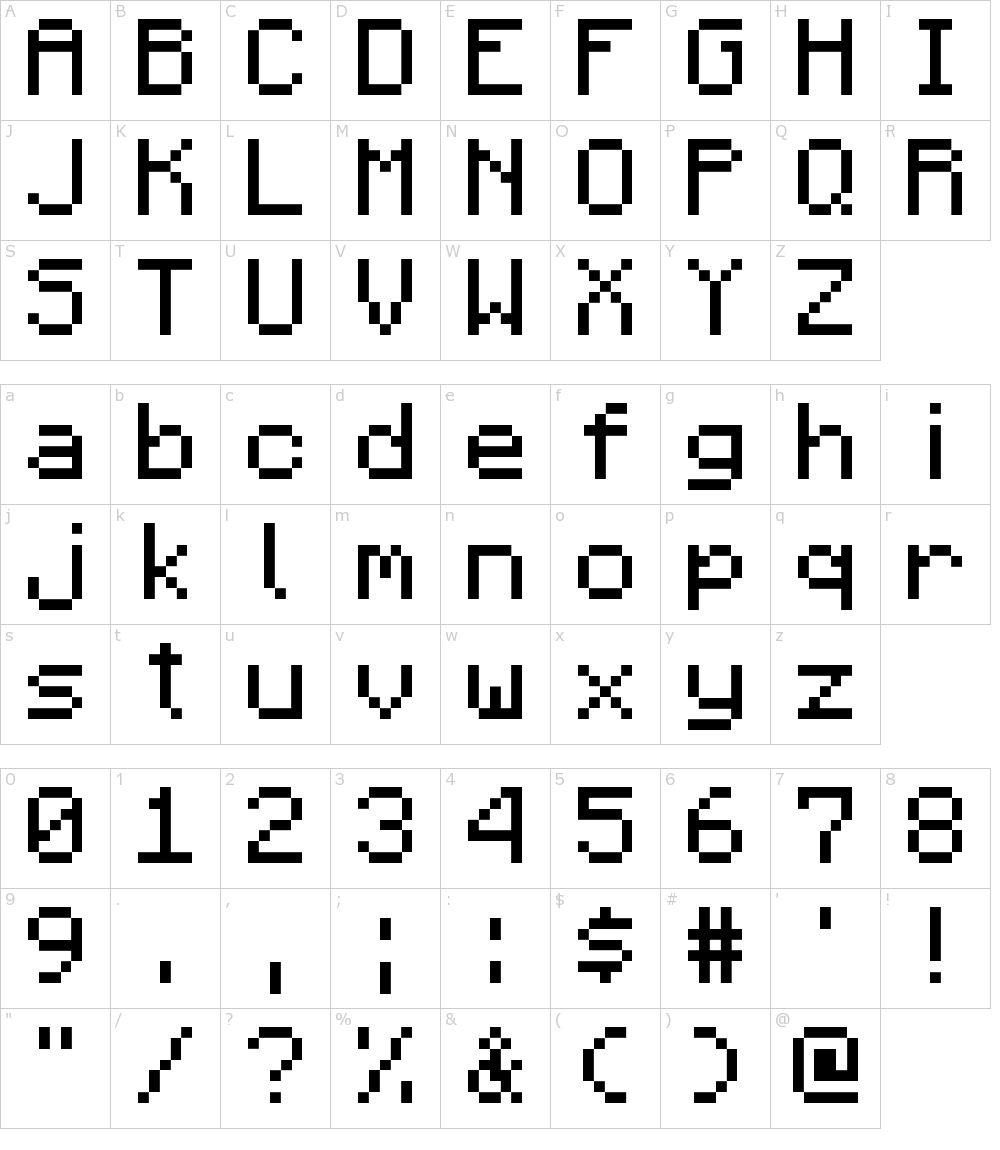
Phân loại: Độc đáo
Kiểu chữ: Sans-Serif
Độ dày: Thin, Light, Regular, Medium, Bold, Black
Font Minecraft là một font chữ đặc trưng, gắn liền với tựa game nổi tiếng cùng tên, được biết đến với phong cách pixel art đặc trưng. Font chữ này tái hiện hoàn hảo giao diện pixelated của trò chơi, mang đến cảm giác hoài cổ và đơn giản, gợi nhớ đến thiết kế đồ họa 8-bit cổ điển. Font Minecraft là font chữ thuộc bộ font chữ design thường được sử dụng trong các thiết kế liên quan đến game, đặc biệt là khi muốn tạo ra sự kết nối trực tiếp với thế giới blocky và sáng tạo của Minecraft. Đây là lựa chọn lý tưởng cho các dự án thiết kế cần sự độc đáo, sáng tạo, và mang tính biểu tượng mạnh mẽ.